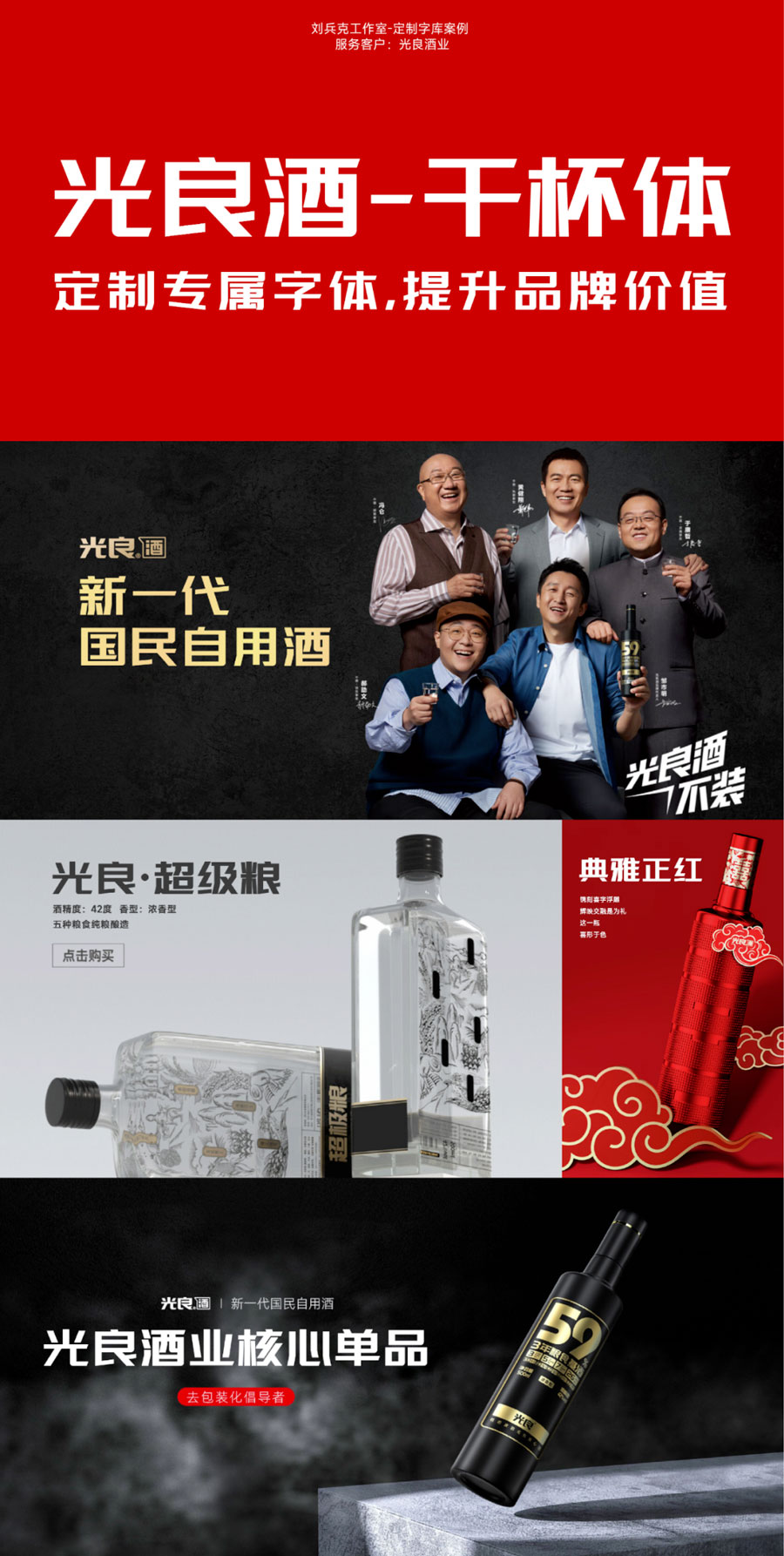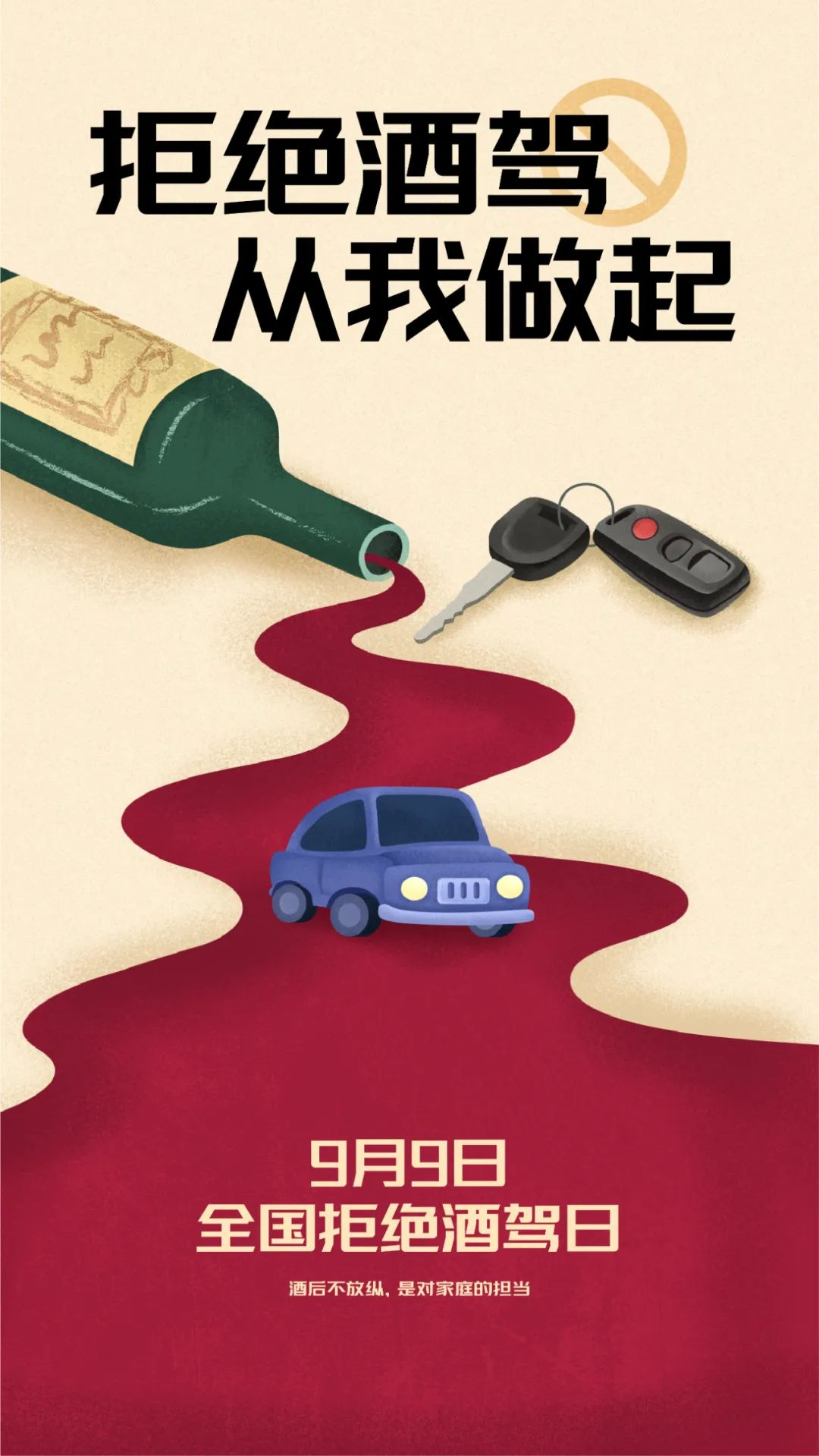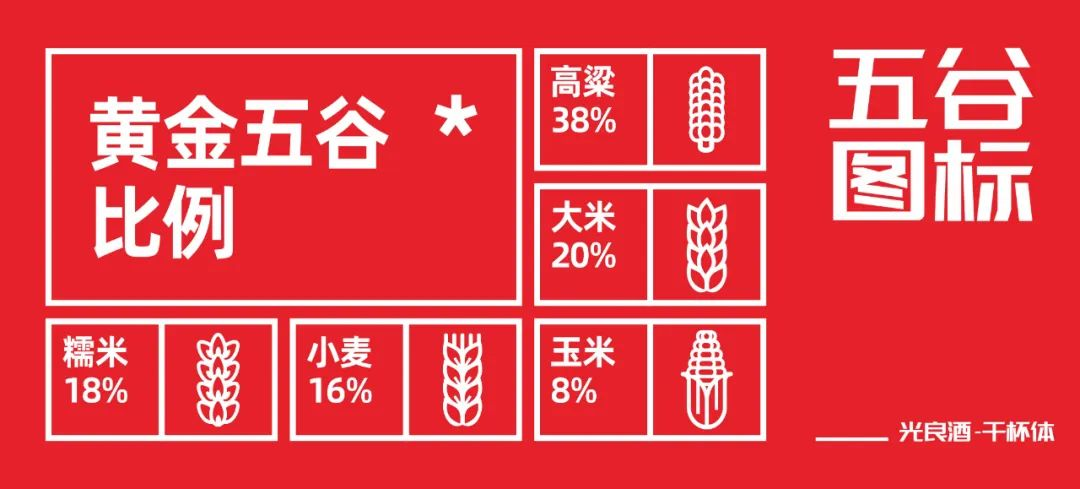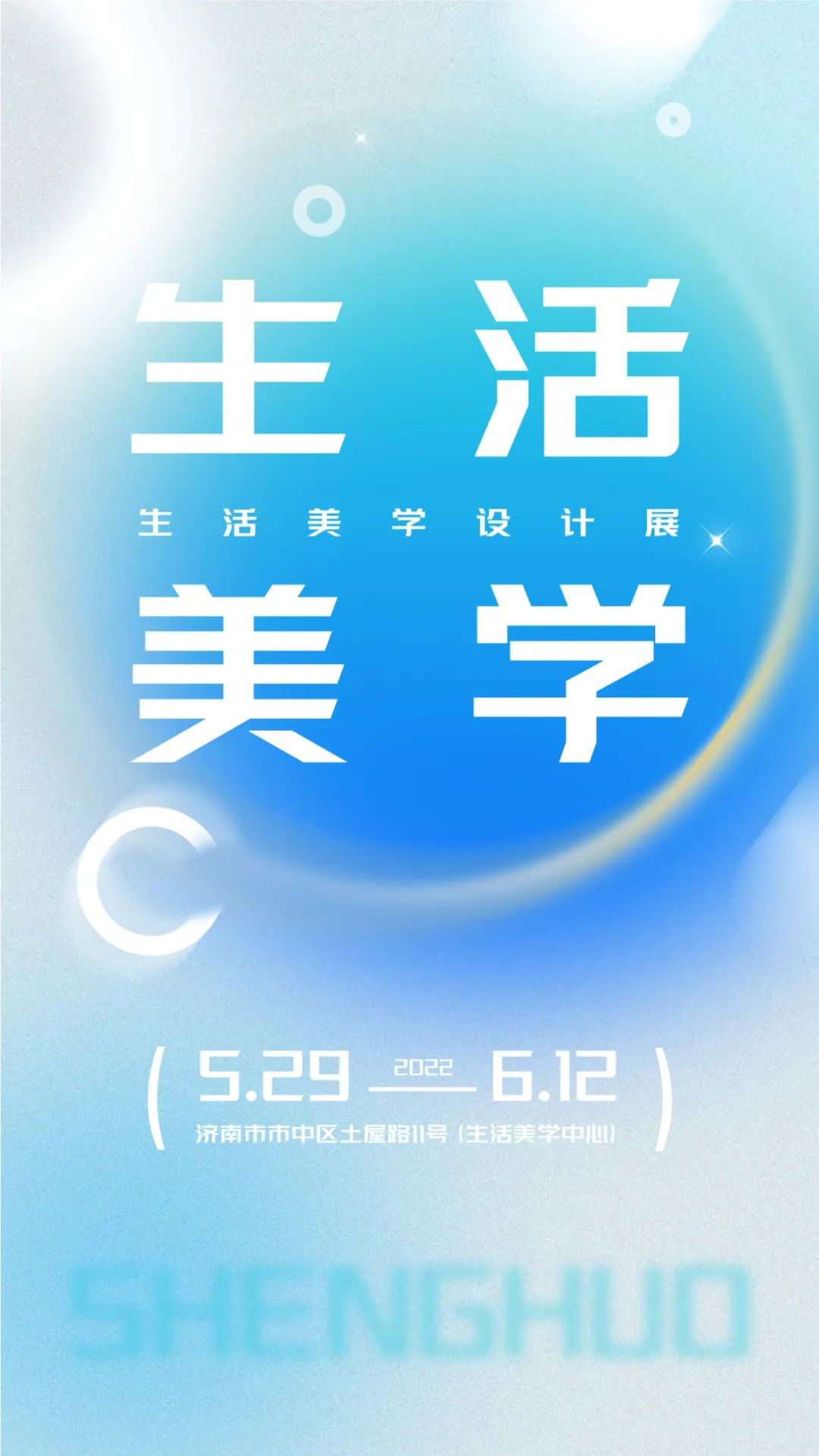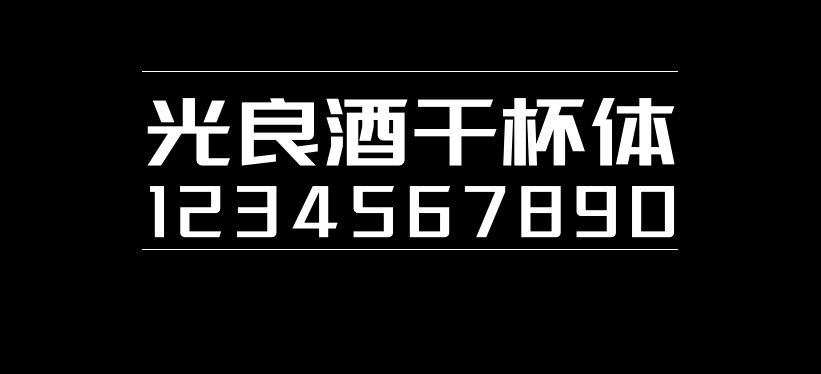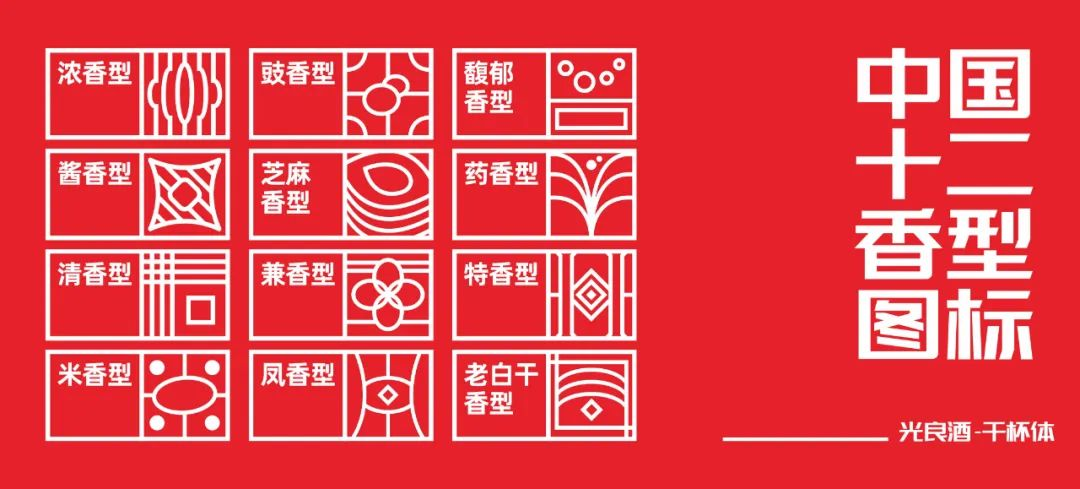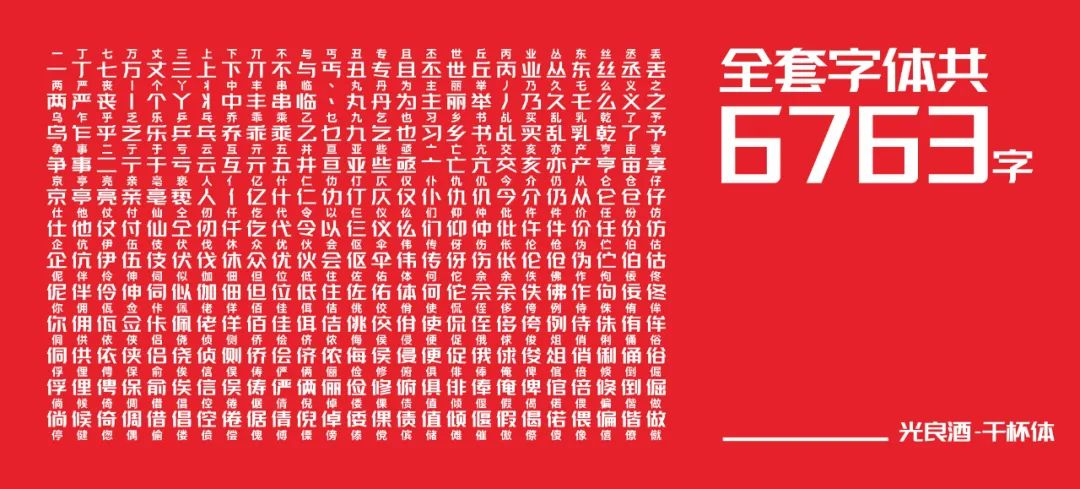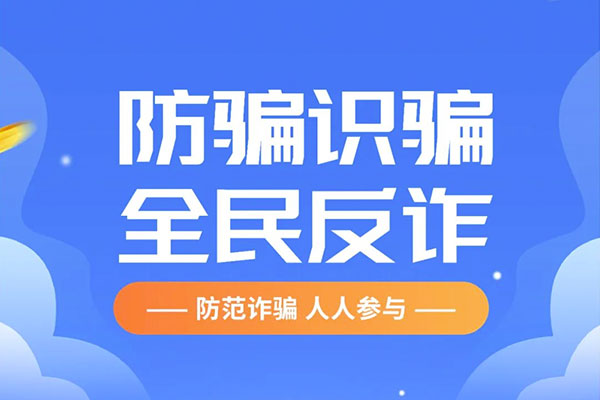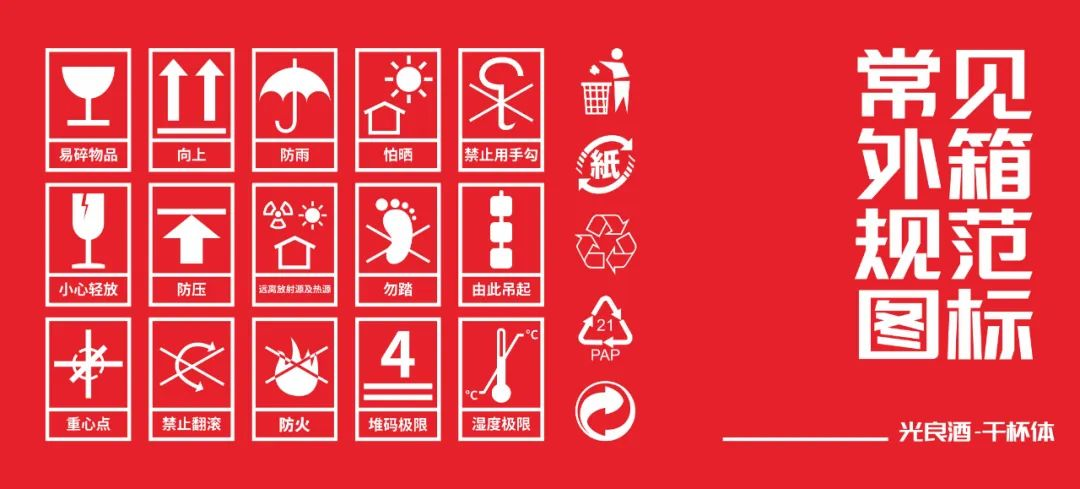
光良酒干杯体
是光良酒业委托刘兵克字体工作室设计制作的一款免费商用字体。
您可以会疑惑,为什么一家白酒企业要做一款定制字库,而且!还要免费开放给社会使用呢?
下面这张截图,就是其中的一个原因:
光良酒干杯体
对大部分品牌来说,以微信公众号为代表的自媒体平台已然成为被控“侵权”的高发阵地,而其中首当其冲的便是字体侵权。当因为无意间使用而被控“侵权”及索赔时,品牌方不得不删除辛苦产出的内容,或者向索赔方支付高额的赔偿,只有这样,才能让索赔方消消气,品牌方也才能避开一次次的“律师函问候”,用钱换来安生……
此类事件频繁发生,给企业造成了非常大的困扰,甚至不得不求助于专业的维权机构,耗费了较多的时间和精力。
而之所以造成这样的情况,品牌方之所以不小心用上了这种“需要赔钱才能了事”的字体,很大一部分原因就是因为字库厂商的“碰瓷式维权”和“钓鱼执法”……
所以,光良酒业,这次来了一次超级霸气的操作:
开发一套字库出来,
而且允许全社会免费商用!
这样的企业,真是够爽朗够大气!
支付给我们几十万开发字库,我当然很开心,字库开发完成,还免费开放商用,所有人都开心!额~这样的企业,越多越好!图片
好了,接下来,就给大家展示一下这款光良酒-干杯体:
光良酒干杯体
这是一款很好用、很实用的标题类字库,用作标题字会非常方便,而且通用性很强,可以说是适合任何行业。
执行的是GB2312标准,包含简体6763字+其他字母字符等。
同时,还包含了55个酒字的设计,以及五谷图标、十二香型、外箱规范等酒类包装的常用素材!酒行业的设计师同行们,用起来更是极为方便!
光良酒干杯体